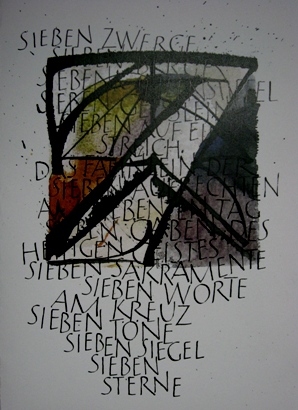
インゲさん!
ドイツのカリ人Ingeborg(インゲボルク)のことは、勝手にインゲと
呼んでます・・・。何も知らないインゲ・・・。ごめんなさい。
ずいぶん前に日本でWSをしてもらった時には、家族の話で
息子さんもずいぶん大きかったから・・・と月日は流れ・・・。
今年になって届いたグリーティングカードは何やら特別?
とてもセンスの良いかっこいい
レターとカード!
ふ〜む…何々?70回目の誕生日とな!ほほ〜だから今年は特別の
Neujahrskarte(新年のグリーティングカード)を作ったそうです!
なるへそ…確かにカードは七づくしの言葉が書いてありますよぉ〜。
SIEBENと読めるのが「7」です。
デザインも「7」ですね〜。
彼女が説明していた「Einladung」
(招待状)は、多分右?
グーテンベルグミュージアム脇の活版印刷工房で作ったとな!
ほほ〜Neulandの文字がかわいい!コントラストで綴られている
カーシブ文字の高さや…少し違うかもしれませんが、mojitor-sさんのやったグラデーションにも通じる部分がありそう〜。組み合わせの妙です!濃く見える部分と薄く見える部分のバランスが美しい〜!![]()